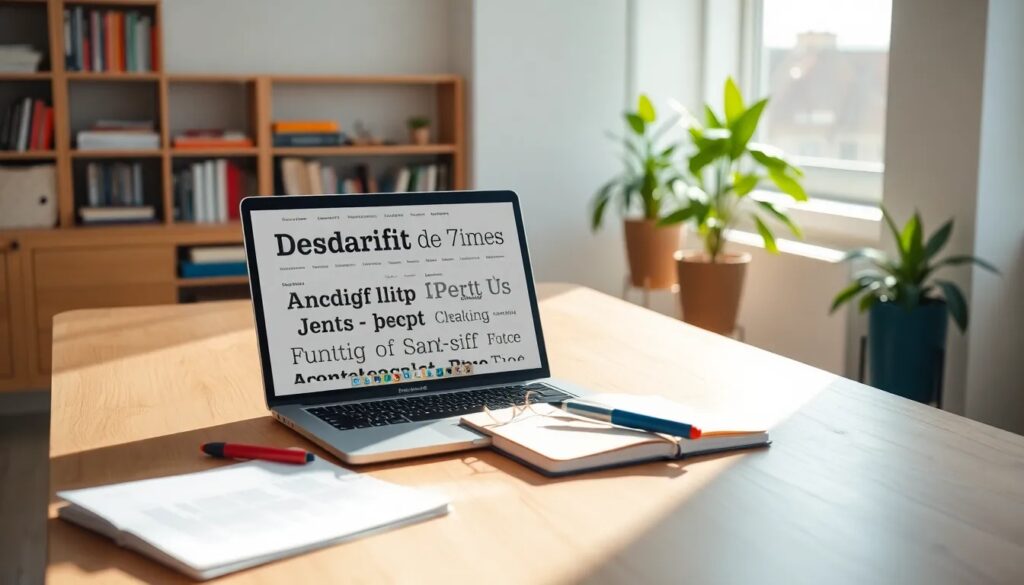
Descargar fonts gratis: las mejores opciones disponibles
Si eres un diseñador gráfico o simplemente te apasiona el mundo de la tipografía, seguramente te has preguntado cómo descargar fonts de manera efectiva y gratuita. Contar con una variedad de fuentes puede llevar tus proyectos al siguiente nivel, ya sea para presentaciones, diseños o contenido digital.
A continuación, exploraremos todo lo que necesitas saber sobre las fuentes de letras, desde cómo encontrarlas hasta cómo instalarlas en tu ordenador. Prepárate para sumergirte en un mundo de creatividad tipográfica.
¿Qué son las fuentes de letras?
Las fuentes de letras, también conocidas como tipografías, son conjuntos de caracteres que comparten un mismo diseño estilístico. Estas pueden variar en grosor, forma y estilo, y se utilizan para comunicar mensajes visualmente atractivos.
Dentro de las fuentes, podemos encontrar diferentes categorías, como fuentes elegantes, tipografías modernas y fuentes vintage. Cada una de ellas aporta una sensación única a tus proyectos.
Además, las fuentes pueden afectar la legibilidad y la percepción del mensaje. Por ello, es crucial elegir la fuente adecuada según el contexto y el público objetivo.
¿Dónde puedo descargar fuentes gratis?
Hoy en día, existen numerosas plataformas donde puedes descargar fonts gratis. Algunas de las más reconocidas incluyen:
- 1001 Free Fonts
- Dafont
- Google Fonts
- Urban Fonts
- Font River
Estos sitios ofrecen una amplia variedad de fuentes tipográficas que son gratuitas, algunas incluso permiten su uso comercial. Navegar por estas plataformas es sencillo, y generalmente puedes filtrar por estilos o categorías.
Por ejemplo, en Google Fonts puedes encontrar tipografías que se adaptan perfectamente a páginas web, mientras que Dafont se especializa en fuentes decorativas y temáticas. Asegúrate de revisar cada licencia antes de usar las fuentes en tus proyectos.
- Dominio público: Puedes usar la fuente sin restricciones.
Es fundamental leer los archivos "Readme" que suelen venir incluidos con las fuentes. Allí encontrarás información específica sobre el uso y las restricciones de cada tipografía.
¿Cuáles son las mejores páginas para descargar fuentes?
Existen diversas páginas que se destacan por ofrecer una gran variedad de fuentes gratis. Algunas de las más recomendadas son:
- 1001 Free Fonts: Con más de 96,000 fuentes, es un recurso invaluable para diseñadores.
- Dafont: Ideal para encontrar fuentes creativas y temáticas.
- Google Fonts: Perfecto para integrar tipografías en sitios web.
- Font Squirrel: Ofrece fuentes seleccionadas que son seguras para uso comercial.
- Behance: Muchos diseñadores comparten sus tipografías aquí, ideales para proyectos únicos.
Estas plataformas no solo te permiten descargar fuentes, sino que también ofrecen herramientas para previsualizarlas en diferentes contextos, facilitando la elección de la más adecuada para tu proyecto.
¿Qué aplicaciones puedo usar para cambiar fuentes en mis mensajes?
Transformar tus mensajes ordinarios en obras visuales llamativas es fácil gracias a diversas aplicaciones disponibles. Algunas de las más populares incluyen:
- Canva: Permite cambiar fuentes fácilmente y ofrece una variedad de estilos.
- Adobe Spark: Ideal para crear gráficos atractivos con tipografías personalizadas.
- Word: Puedes cambiar fuentes directamente en tus documentos de texto.
- Instagram: Esta red social permite utilizar diferentes estilos de texto en las historias.
Estas herramientas son perfectas para quienes buscan descargar fuentes para Canva y utilizarlas en sus diseños. Al incorporar tipografías creativas, puedes mejorar la estética de tus publicaciones y atrapar la atención de tu audiencia.
Preguntas relacionadas sobre la descarga de fuentes gratis
¿Dónde puedo encontrar fuentes de letras gratis?
Hay varias plataformas donde puedes descargar fonts gratis. Sitios como Dafont, 1001 Free Fonts y Google Fonts son ideales para encontrar una amplia variedad de tipografías. Además, asegúrate de revisar las licencias para conocer los usos permitidos de las fuentes que elijas.
¿Cómo puedo descargar fuentes de letras gratis para copiar y pegar?
Para descargar fuentes de letras gratis, simplemente visita alguno de los sitios mencionados, elige la fuente que desees y sigue las instrucciones para descargarla. Después de descargarla, la podrás instalar en tu sistema operativo y utilizarla en aplicaciones de texto o de diseño.
¿Es seguro descargar fuentes de Adobe Fonts gratis?
En general, descargar fuentes de Adobe Fonts es seguro, siempre y cuando lo hagas desde la plataforma oficial de Adobe. Este servicio ofrece una gran variedad de fuentes que puedes utilizar en tus proyectos, pero es esencial seguir las indicaciones de uso y licencias específicas. Las fuentes de Adobe suelen ser de alta calidad y están diseñadas para un uso profesional.
¿Puedo descargar fuentes gratis para Canva?
Sí, Canva permite descargar fonts de diversas plataformas y utilizarlas en sus diseños. Si tienes una fuente específica que te gusta, puedes buscarla en sitios como Google Fonts y luego subirla a Canva. Esto te permitirá personalizar tus proyectos de manera efectiva.